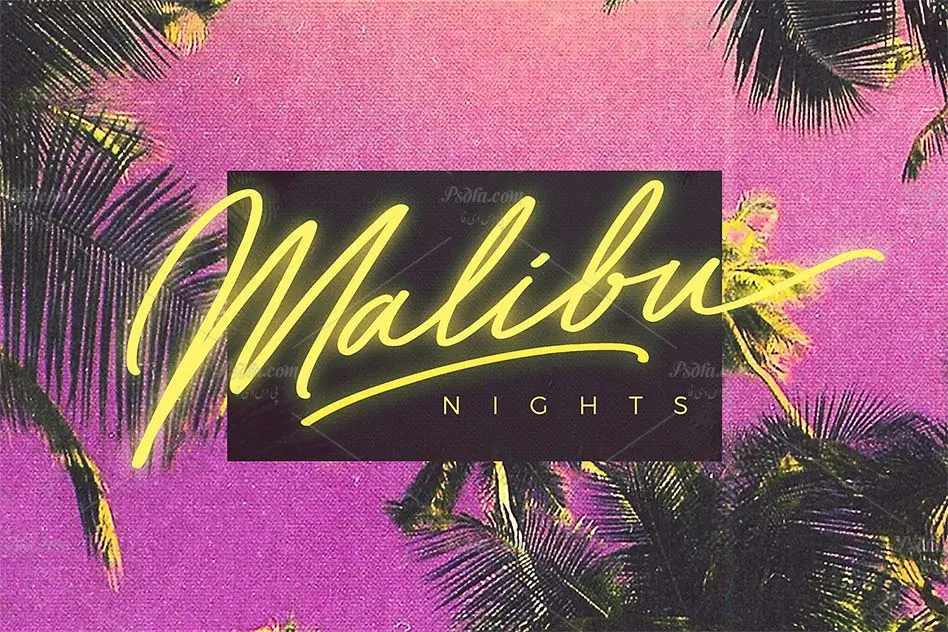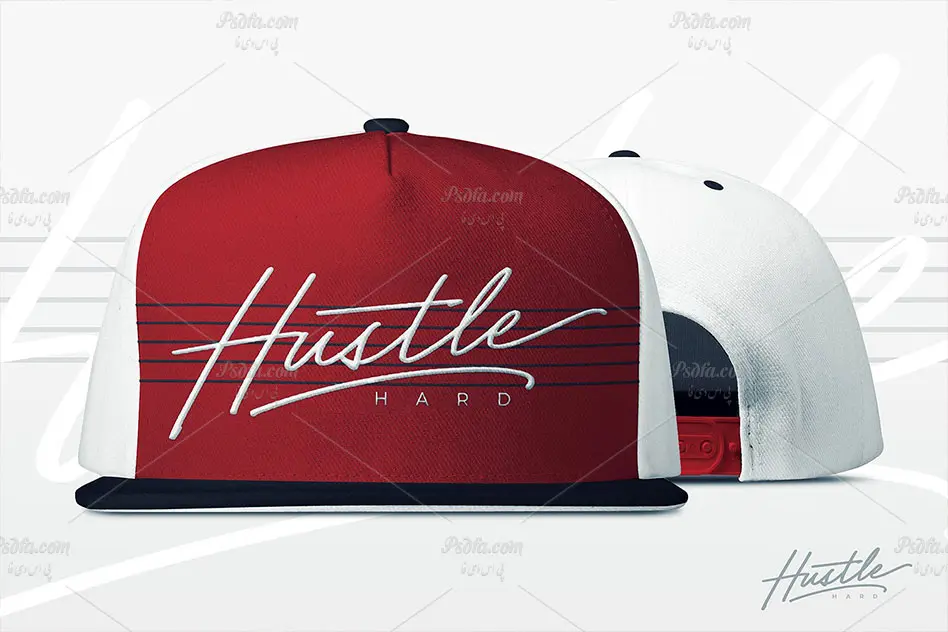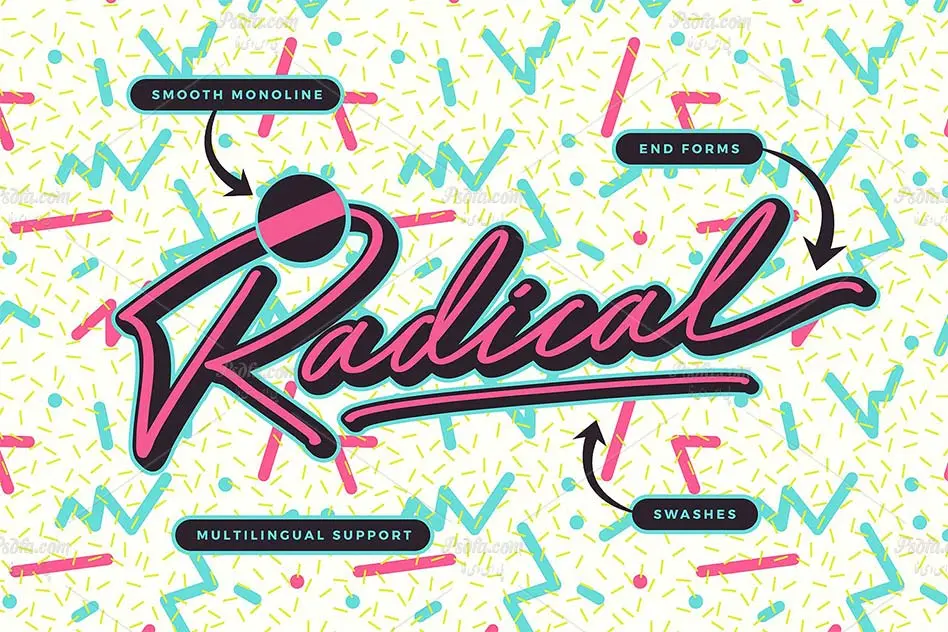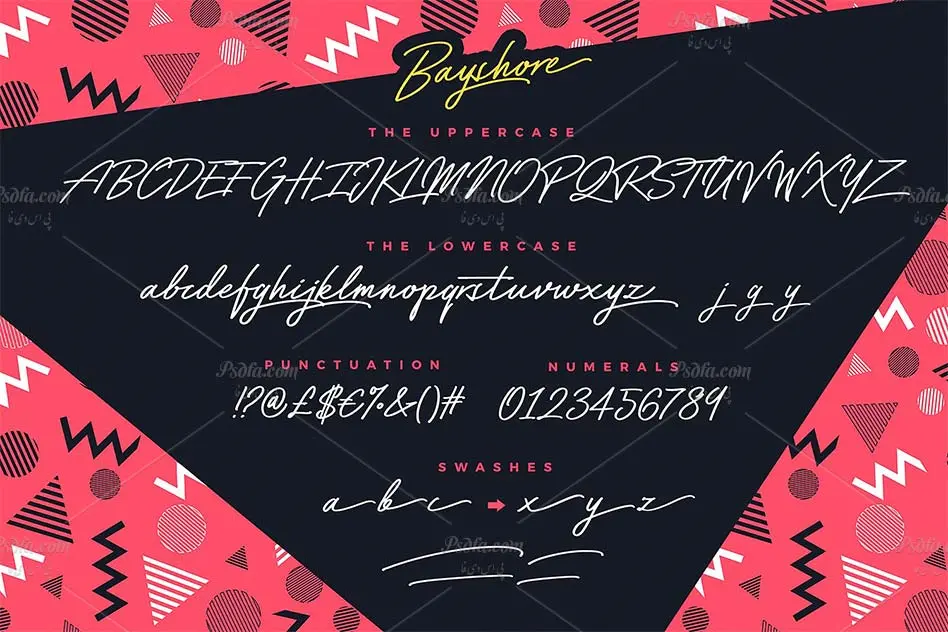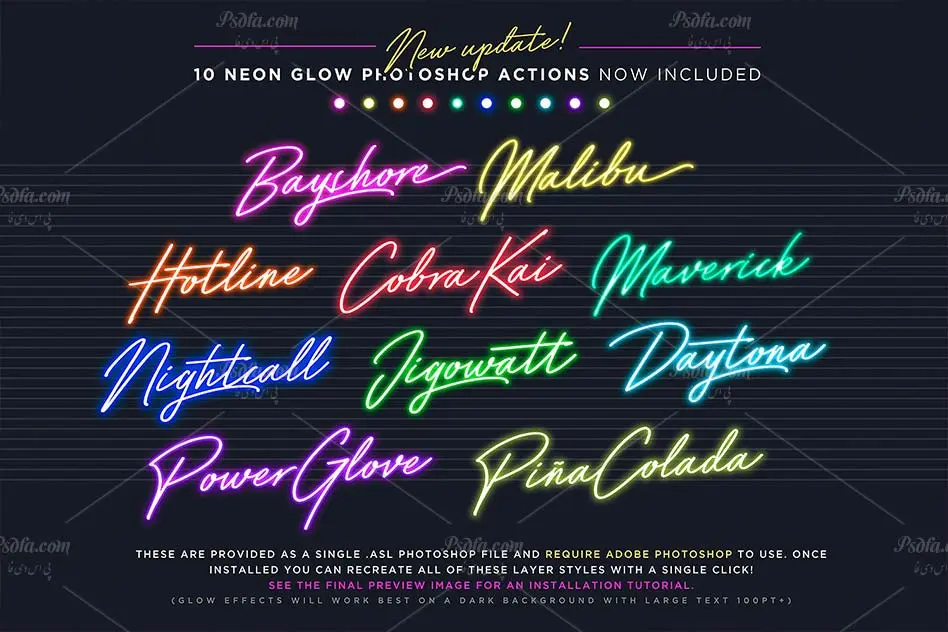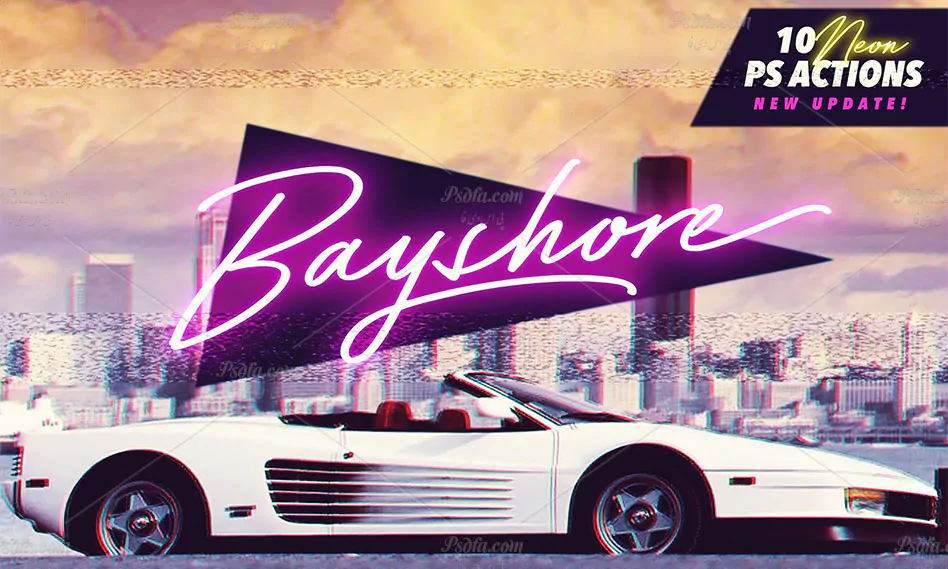
در این مطلب شاهد فونت انگلیسی دستنویس Bayshore مناسب جهت استفاده در طراحی و گرافیک می باشید. این فونت فوق العاده زیبا در قالب 2 فایل ttf و otf در سایت بارگذاری شده اند که با نصب هر یک از این دو فایل در پوشه فونت های سیستم خود قادر به استفاده مستقیم از این فونت زیبا در تمام نرم افزار های گرافیکی و ویرایشگر متن از جمله نرم افزار فتوشاپ ، مجموعه نرم افزار آفیس و … می باشید. از این فونت زیبا که در سبک فونت های دستنویس طراحی شده است می توان در ایجاد طرح های گرافیکی به خصوص انواع کاور و پوستر ، طراحی بنر ، تراکت ، کارت ویزیت و … استفاده نمود.